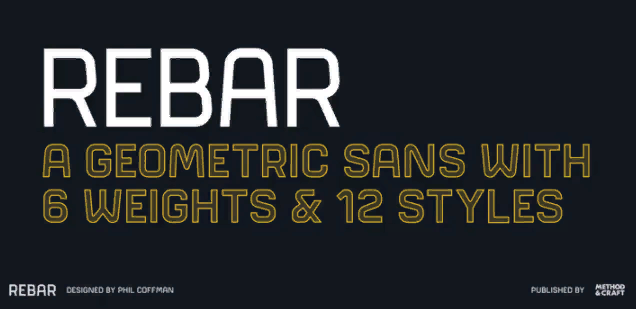
[Myfonts] Rebar Font Family (2021)
Название: Rebar Font Family (2021)
Состоящий из 6 весов и 12 стилей, Rebar - это геометрический санс с гармоничными кривыми и слегка наклоненным обрамлением, которое придает шрифту баланс и силу. Включает цифры, пунктуацию, некоторые лигатуры и диакритические знаки для совместимости со многими иностранными языками.